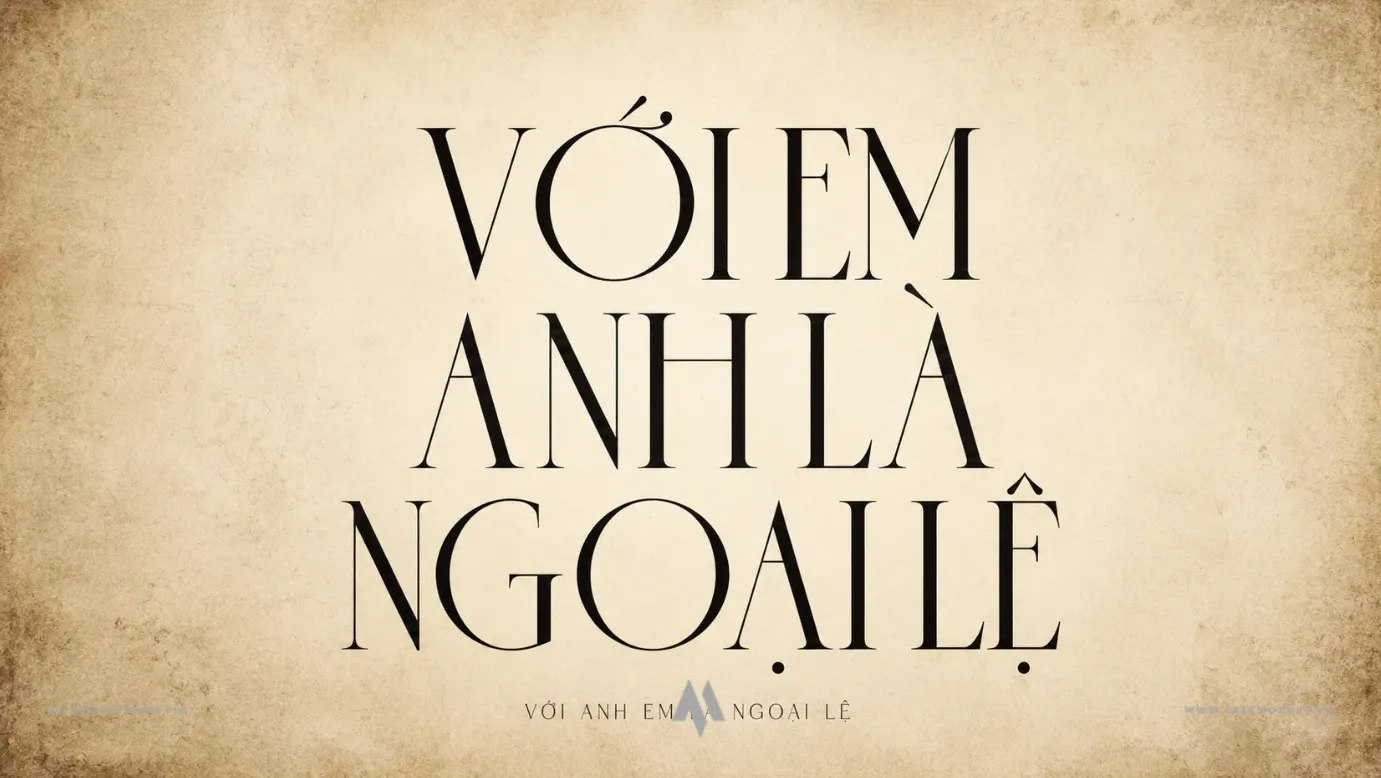
Font DFVN Sauvage việt hóa – Thanh lịch, hiện đại
Font DFVN Sauvage Việt Hóa là bộ font chữ có chân (Serif) cao cấp lấy cảm hứng từ phong cách nghệ thuật Art Deco, mang đến sự kết hợp hoàn hảo giữa nét cổ điển thanh lịch và tinh thần hiện đại, thời thượng. Với cấu trúc chuẩn mực cùng các đường nét cách điệu tinh xảo, bộ font là lựa chọn lý tưởng để tạo nên bản sắc thị giác độc đáo cho mọi tác phẩm thiết kế.
Đặc điểm nổi bật
• Nguồn cảm hứng Art Deco độc đáo: Từng ký tự sở hữu độ tương phản sắc nét, đường nét mềm mại nhưng vẫn giữ được sự vững chãi, rõ ràng và phóng khoáng.
• Tỉ lệ cân đối chuẩn xác: Khoảng cách và cấu trúc chữ được tính toán tỉ mỉ, giúp tối ưu khả năng đọc và tạo hiệu ứng thị giác ấn tượng ở cả kích thước lớn lẫn tiêu đề phụ.
• Việt hóa chuẩn chỉnh: Đầy đủ hệ thống ký tự và dấu tiếng Việt, tương thích mượt mà trên các công cụ thiết kế phổ biến như Adobe Photoshop, Illustrator, InDesign, Figma và Canva.
Ứng dụng hoàn hảo trong thiết kế
• Nhận diện thương hiệu: Thiết kế logo, bộ nhận diện cao cấp cho ngành thời trang, trang sức, mỹ phẩm, kiến trúc và chuỗi khách sạn/resort.
• Xuất bản & Tạp chí: Tiêu đề bài viết biên tập (editorial), bìa tạp chí, sách nghệ thuật, lookbook và catalogue.
• Bao bì & Nhãn mác: Bao bì sản phẩm cao cấp, tem nhãn thủ công, hộp quà tặng và nhãn chai rượu/nước hoa.
• Ấn phẩm sự kiện & Truyền thông: Thiệp mời trang trọng, poster triển lãm, banner quảng bá và visual marketing trên mạng xã hội.